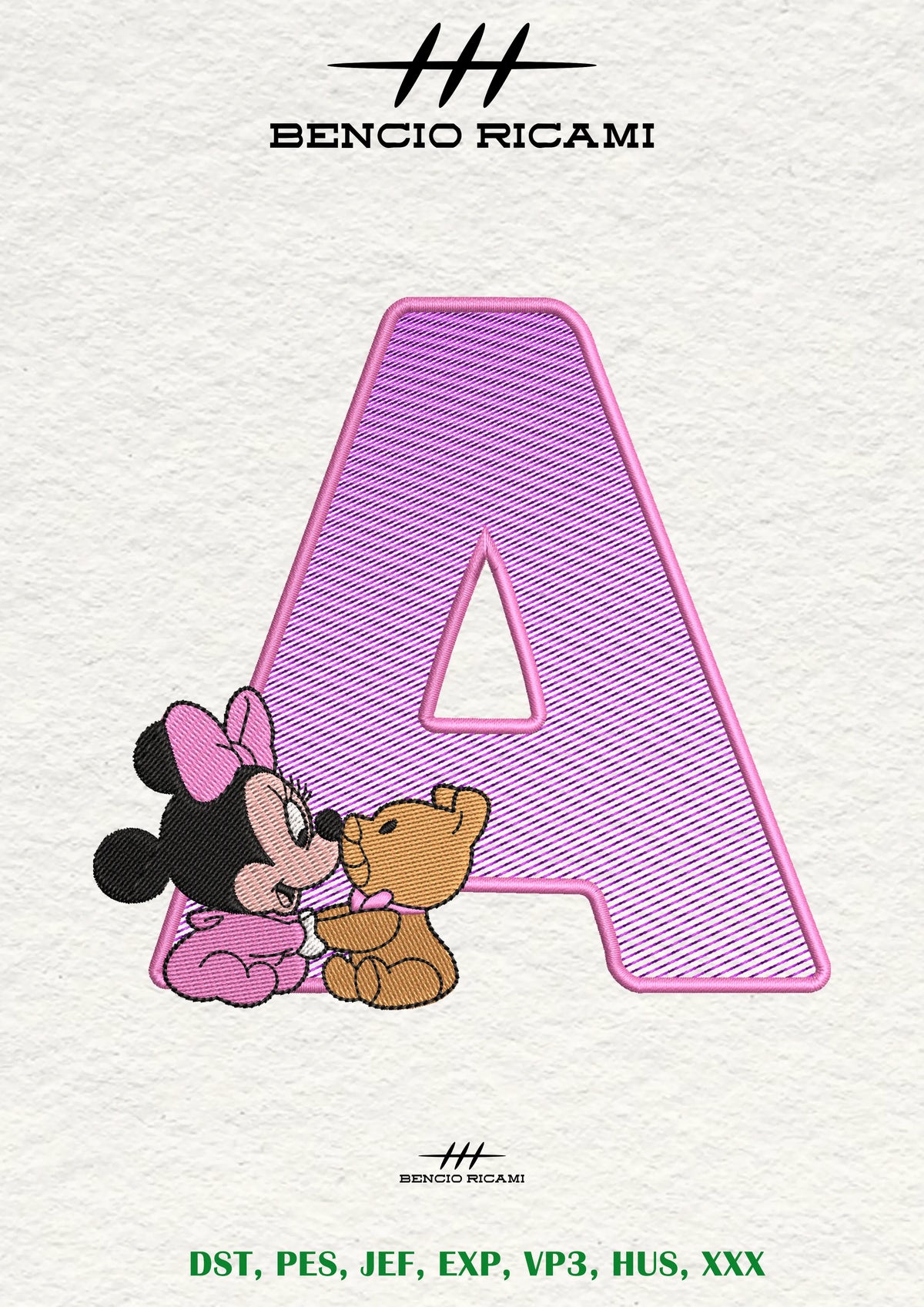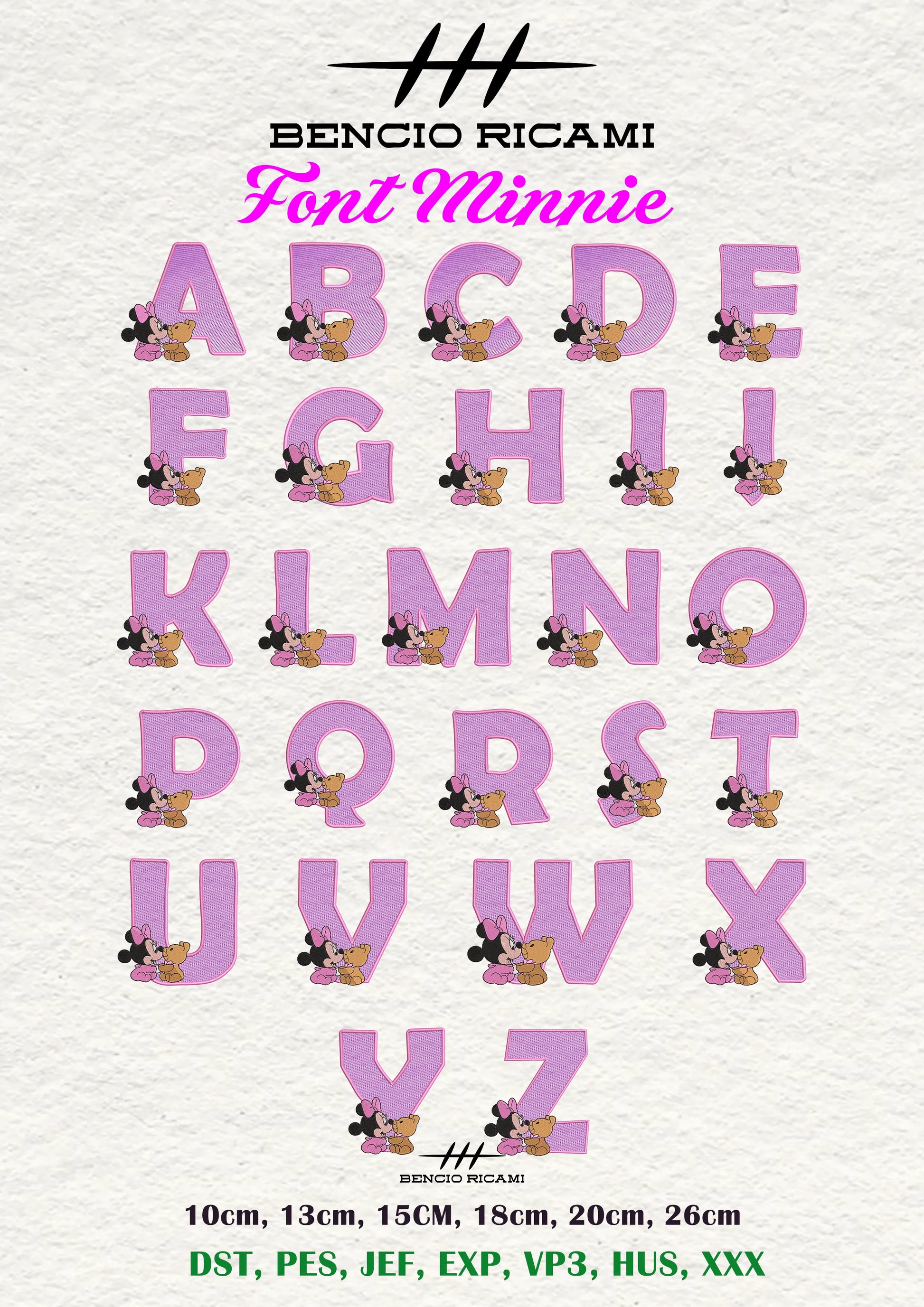
Font ricamo Minnie - BencioRicami
Il font da ricamo Minnie è un alfabeto digitale progettato per ricamatrici domestiche e industriali. Ideale per personalizzare abbigliamento, asciugamani, cappelli, zaini e accessori con ricami precisi e professionali.
Il File è stato digitalizzato con attenzione ai dettagli per garantire un ricamo pulito e ben definito su diversi tipi di tessuto.
✅ Ricamo Dettagliato
✅ 26 lettere maiuscole con elefantino